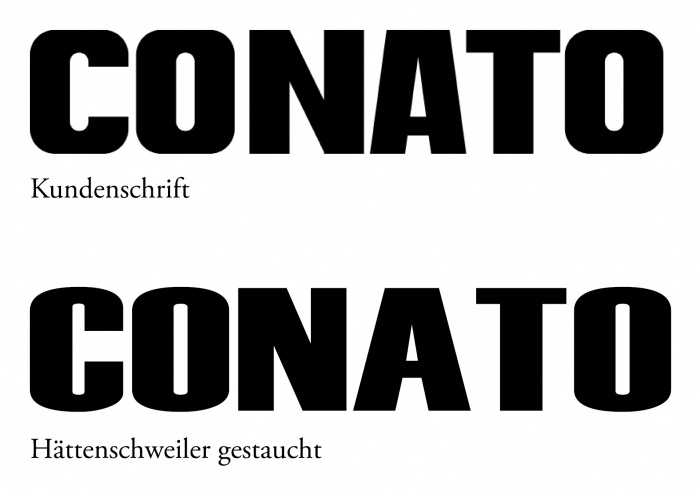
Schrift aus Kunden-Logo
sonst habe ich noch jede Schrift gefunden, diese treibt mich aber zur Verzweiflung.
Ich habe nur ein paar Buchstaben aus dem Logo eines Kunden. Das war schnell nachgezeichnet.
Nur jetzt soll ich Etiketten nachsetzen in denen der Schrift aus dem Logo wieder verwendet wird, was ich vorher nicht wußte.
Die gestauchte Haettenschweiler kommt dem schon recht nah, ich brauche sie aber auch in einer schmalen Variante.
Und da habe ich den Schriftzug schon aufgehübscht nachgezeichnet. Da waren jede Menge Ankerpunkte in den Linien und die runden Ecken völlig ungleichmäßig.
Da die CD ohnehin zur Überarbeitung ansteht kann ich ja mal sehen ob ich die Compacta dann einsetze.
PS. ich sehe gerade, die obere Kante in der nachgezeichneten Kundenschrift ist im Bild angeschnitten. Die habe ich so natürlich nicht gezeichnet.